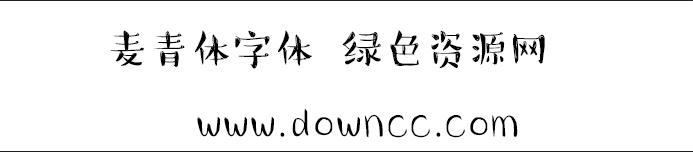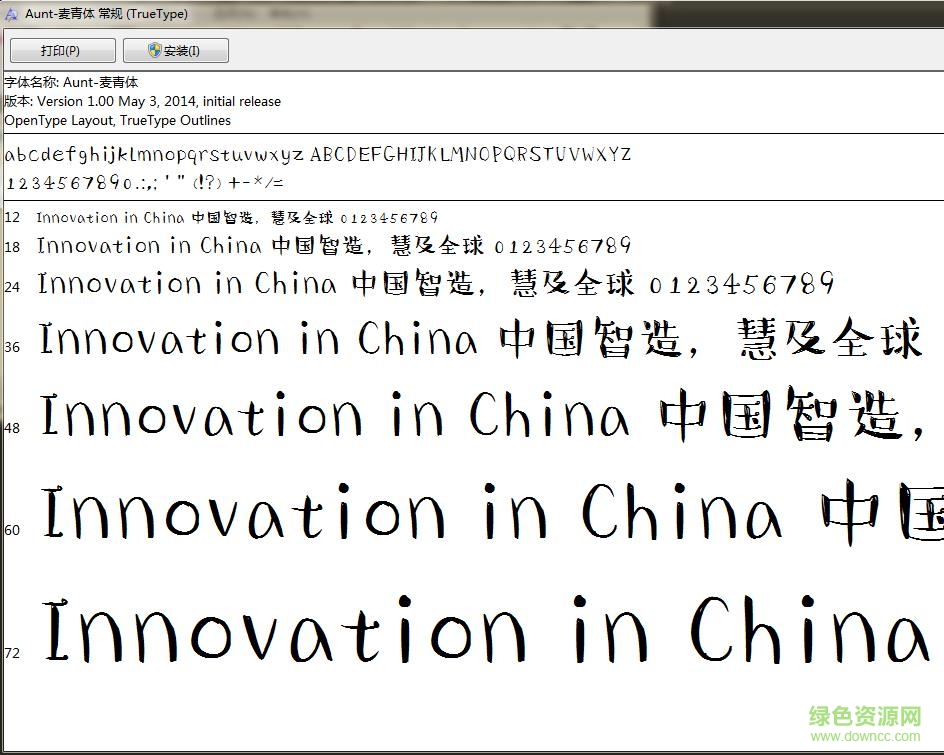
麦青体字体ttf字体风格在众多的字体中都能够受到用户们的喜爱,它的字体拥有一种独特的美感,每一撇每一捺都十分圆润,可以带给你不错的视觉体验!
这款字体的独特之处在于能够让你不断的感受到舒适的体验,字体风格十分圆润,并不锋利,让你在聊天交友过程中以及所需的适当媒体制作中都能够运用!
3、麦青体字体行笔圆转。线条匀净而长。呈现出庄严美丽的风格。